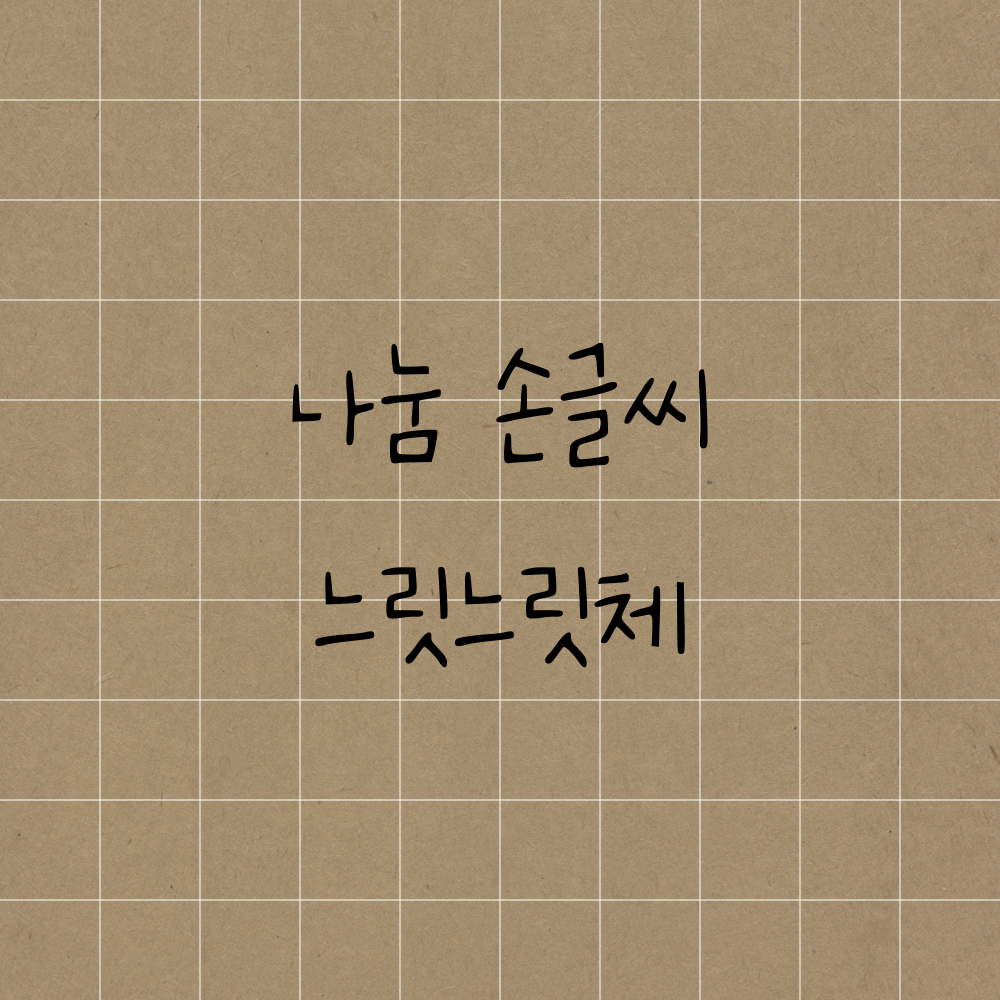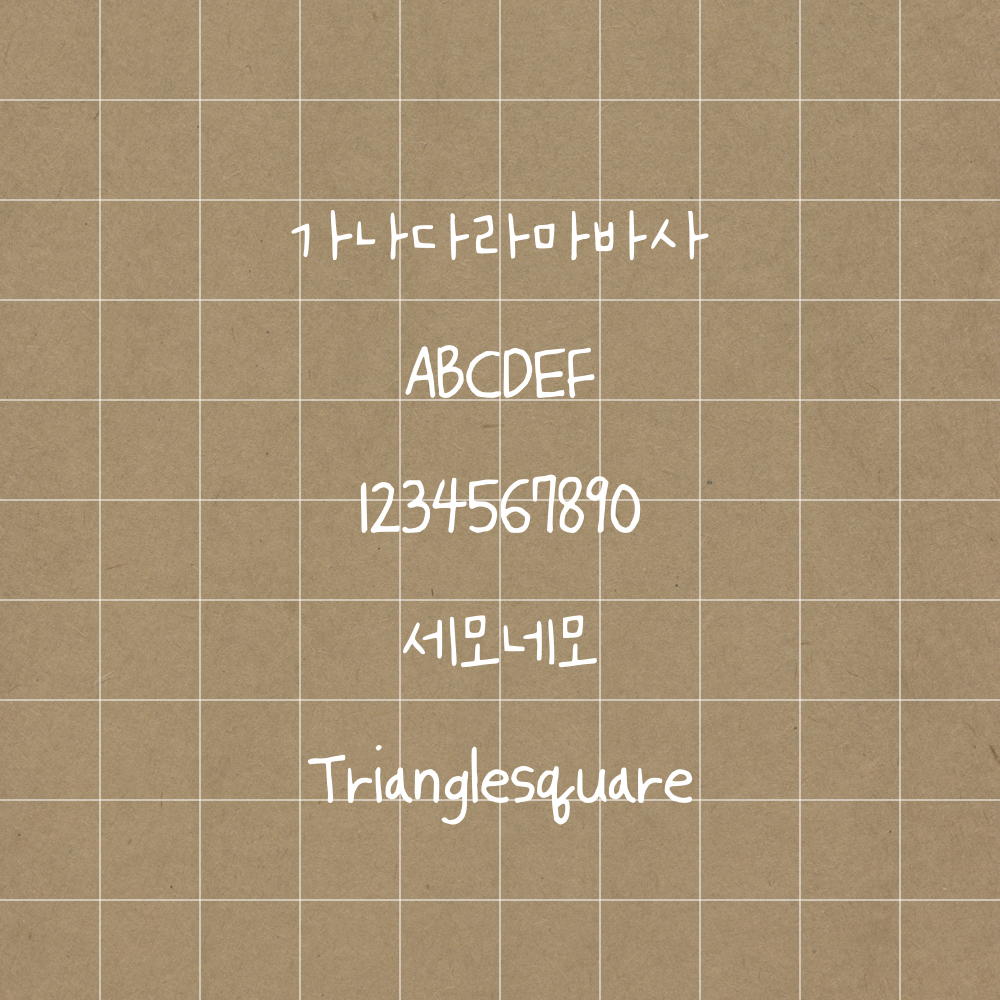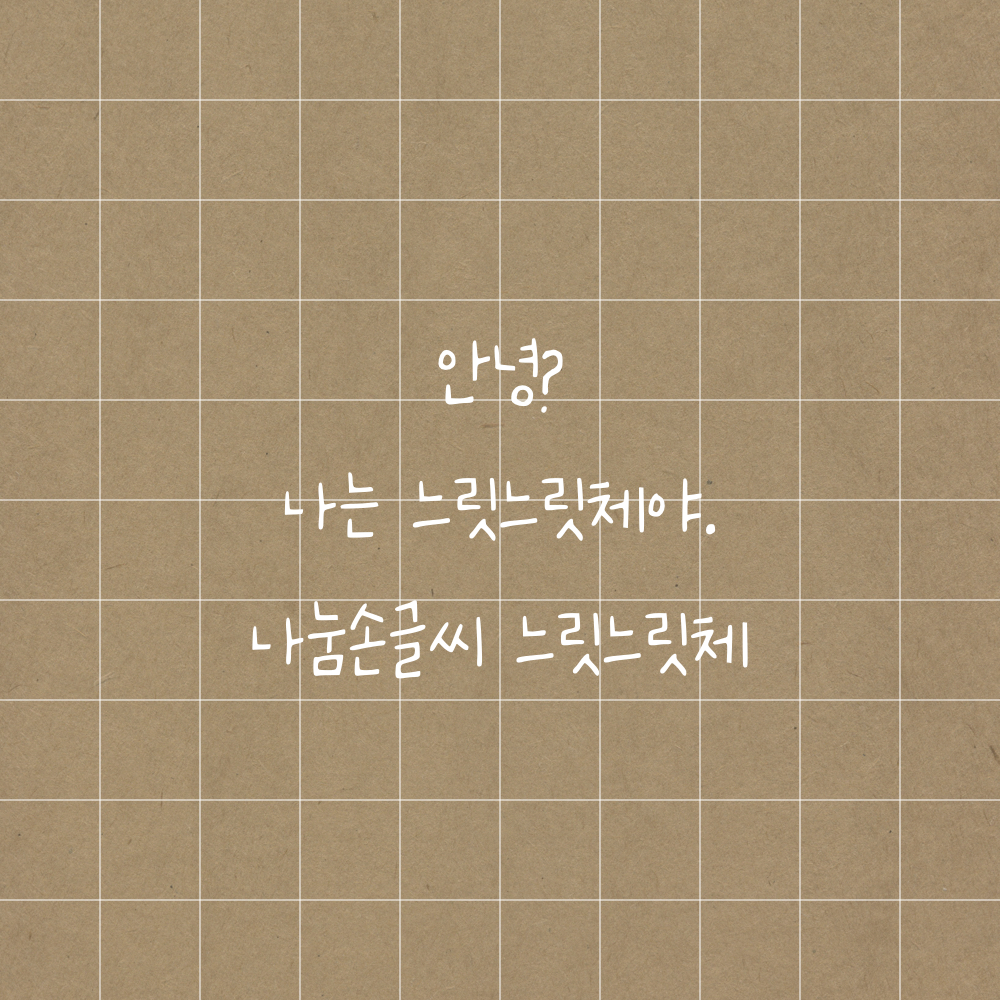
오늘의 폰트는 느릿느릿체입니다💛
최근에 제가 빠진 폰트로 학교 다닐 때, 반에 한 명씩은 있는 프로 필기러들의 글씨체랄까..?
손글씨에 가장 가까워서 매일 사용하고 있습니다😆
세모네모의 최애 폰트 바로 살펴볼까요~?🤓
한국어, 영어, 숫자 예시를 모두 확인해보겠습니다😎
반듯하지만 손글씨만의 인간스러운 글씨체로 필기에 적합한 느릿느릿체